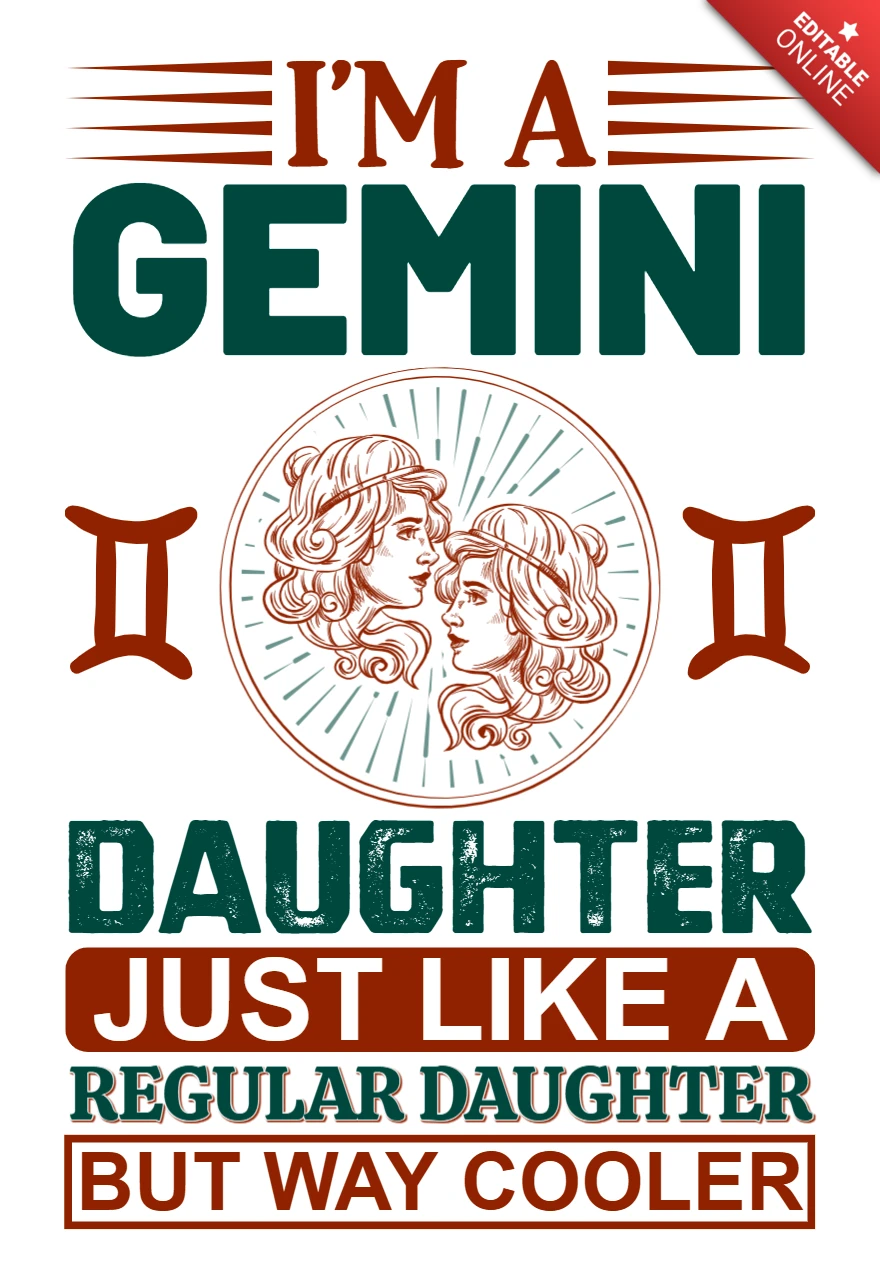
Tweeling dochter vintage typografie ontwerpsjabloon
Bewerken in Design Studio Downloaden in JPGMaak een uniek statement met onze ontwerpsjabloon met gemini thema, perfect om de persoonlijkheid van je dochter te vieren - combineer humor en vintage typografie voor een opvallende poster of merchandise cadeau!